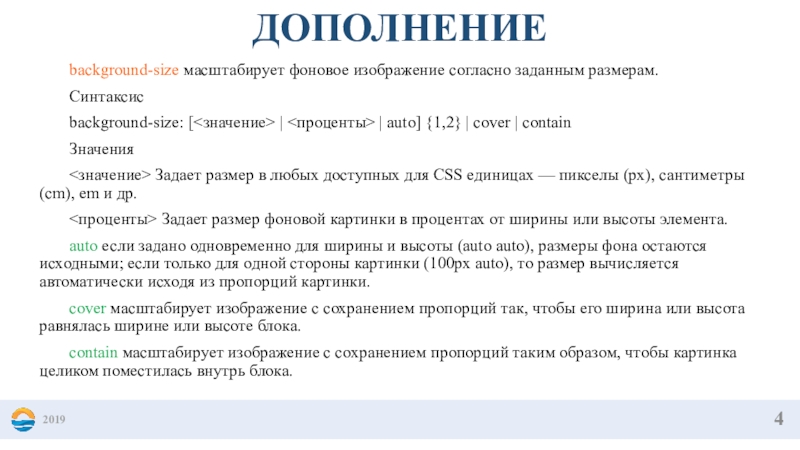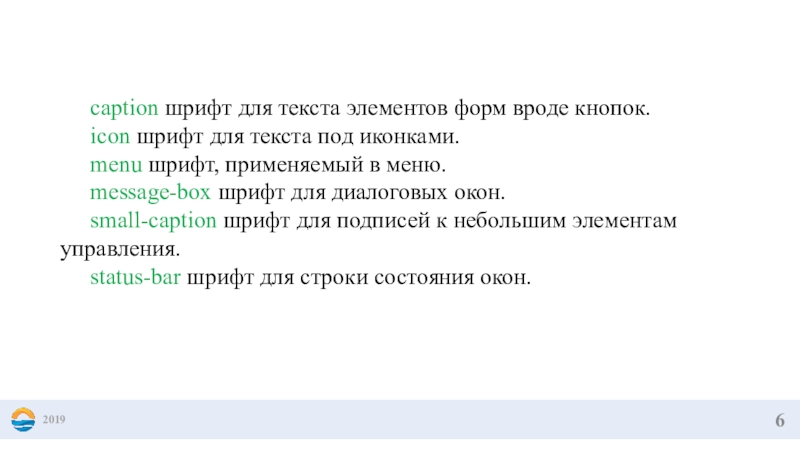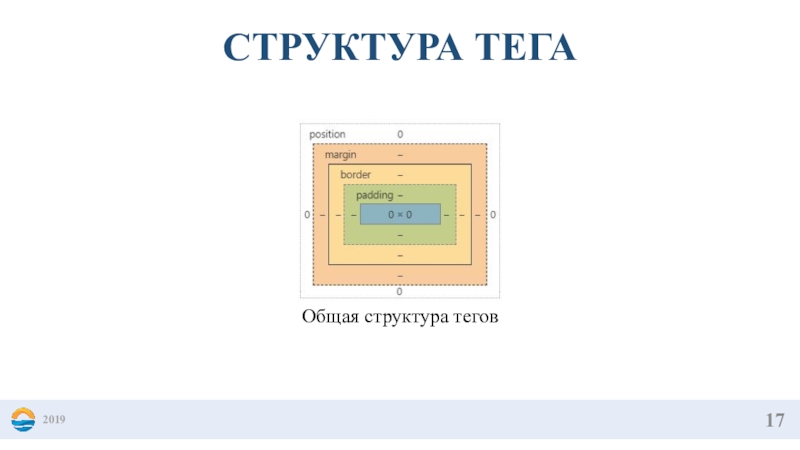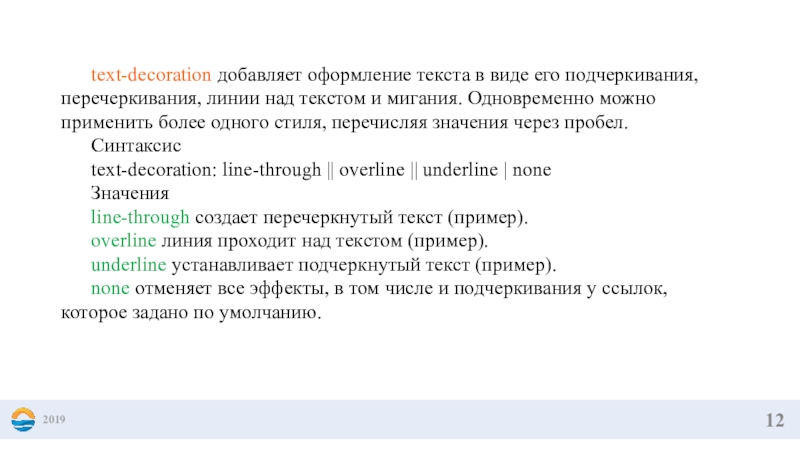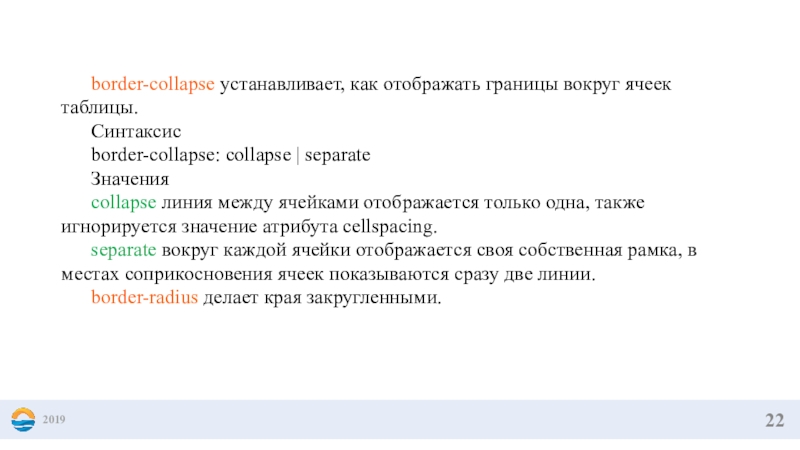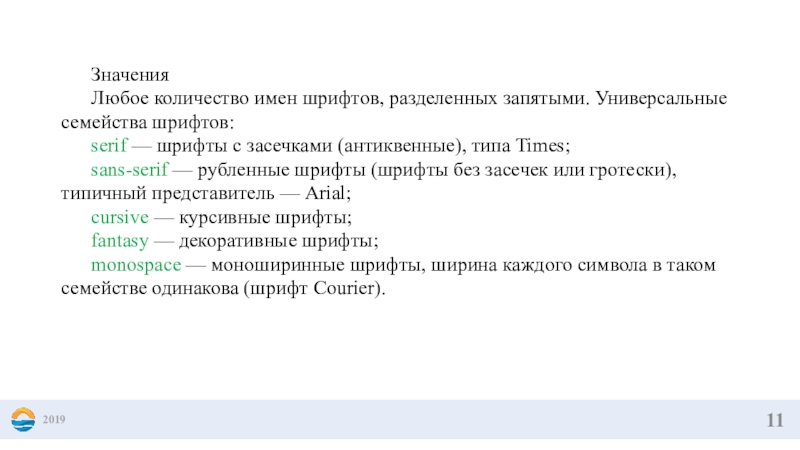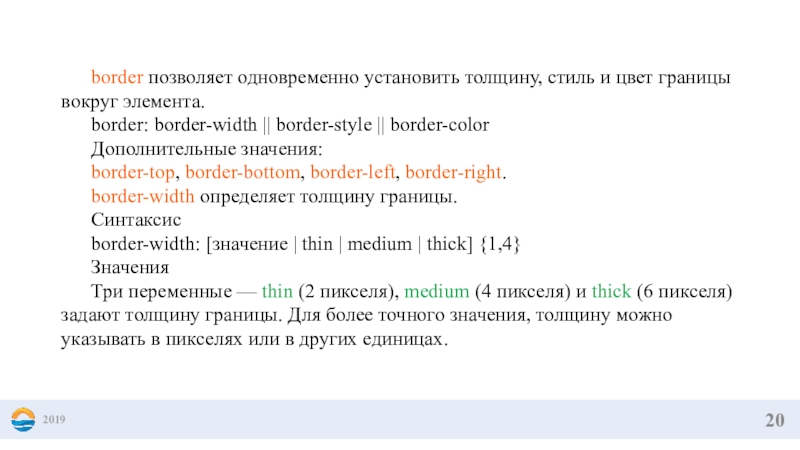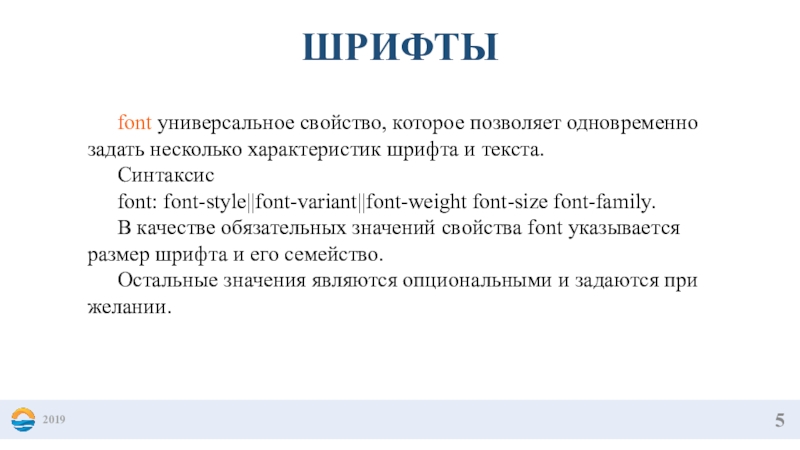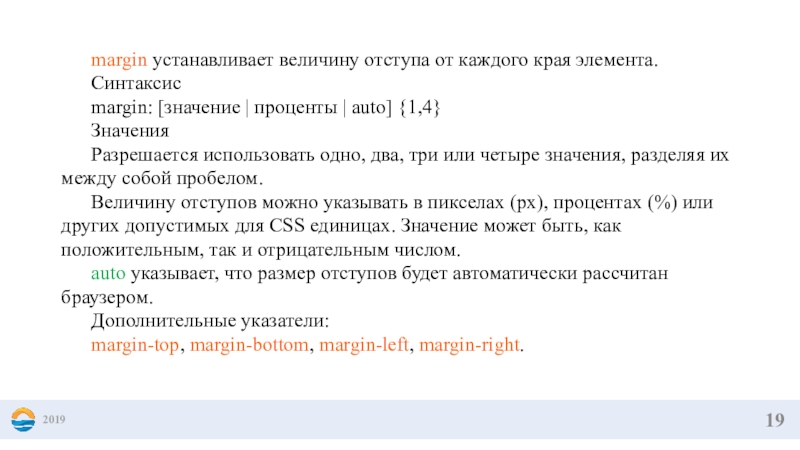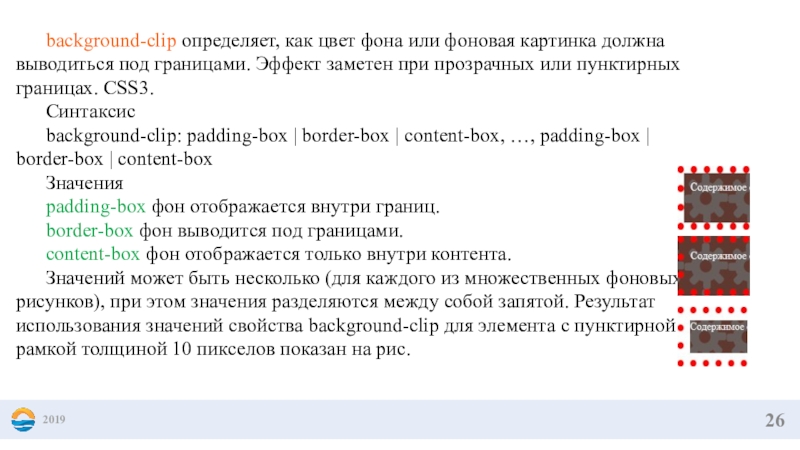
ШРИФТЫ. СТРУКТУРА ТЕГА
px – абсолютные пиксели, к которым привязаны и потому не
нужны mm, cm, pt и pc. Используется для максимально конкретного
и точного задания размеров.
em – задаёт размер относительно шрифта родителя, можно относительно конкретных символов: "x"(ex) и "0"(ch), используется там, где нужно упростить масштабирование компоненты.
pt – Точки традиционно используются в печатных изданиях (т.е. для всего, что печатается на бумаге). Одна точка равняется 1/72 дюйма. Точки очень похожи на пиксели тем, что они имеют фиксированный размер и их нельзя увеличить/уменьшить.
% – относительно такого же свойства родителя (как правило, но не всегда), используется для ширин, высот и так далее, без него никуда, но надо знать, относительно чего он считает проценты.
vw, vh, vmin, vmax – относительно размера экрана. Их основное преимущество – в том, что любые размеры, которые в них заданы, автоматически масштабируются при изменении размеров окна.
2019px – абсолютные пиксели, к которым привязаны и потому не нужны mm, cm, pt и pc. Используется
Слайд 4 background-size масштабирует фоновое изображение согласно заданным размерам.
Синтаксис
background-size: [ |
| auto] {1,2} | cover | contain
Значения
Задает размер в
любых доступных для CSS единицах — пикселы (px), сантиметры (cm), em и др.
<проценты> Задает размер фоновой картинки в процентах от ширины или высоты элемента.
auto если задано одновременно для ширины и высоты (auto auto), размеры фона остаются исходными; если только для одной стороны картинки (100px auto), то размер вычисляется автоматически исходя из пропорций картинки.
cover масштабирует изображение с сохранением пропорций так, чтобы его ширина или высота равнялась ширине или высоте блока.
contain масштабирует изображение с сохранением пропорций таким образом, чтобы картинка целиком поместилась внутрь блока.
ДОПОЛНЕНИЕ
background-size масштабирует фоновое изображение согласно заданным размерам.	Синтаксис	background-size: [ | | auto] {1,2} | cover | contain	Значения	 Задает
ШРИФТЫ
font универсальное свойство, которое позволяет одновременно задать несколько характеристик шрифта
и текста.
Синтаксис
font: font-style||font-variant||font-weight font-size font-family.
В качестве обязательных значений свойства
font указывается размер шрифта и его семейство.
Остальные значения являются опциональными и задаются при желании.
2019ШРИФТЫ	font универсальное свойство, которое позволяет одновременно задать несколько характеристик шрифта и текста.	Синтаксис	font: font-style||font-variant||font-weight font-size font-family. 	В качестве
caption шрифт для текста элементов форм вроде кнопок.
icon шрифт для
текста под иконками.
menu шрифт, применяемый в меню.
message-box шрифт для диалоговых
окон.
small-caption шрифт для подписей к небольшим элементам управления.
status-bar шрифт для строки состояния окон.
2019	caption шрифт для текста элементов форм вроде кнопок.	icon шрифт для текста под иконками.	menu шрифт, применяемый в меню.	message-box
font-style определяет начертание шрифта — обычное, курсивное или наклонное.
Синтаксис
font-style: normal
| italic | oblique
Значения
normal обычное начертание текста. (по умолчанию).
italic
курсивное начертание.
oblique наклонное начертание. Курсив и наклонный шрифт при всей их похожести не одно и то же. Курсив — это специальный шрифт имитирующий рукописный, наклонный же образуется путем наклона обычных знаков вправо.
font-variant определяет, как нужно представлять строчные буквы — оставить их без модификаций или делать их все прописными уменьшенного размера. Такой способ изменения символов называется капителью.
Синтаксис
font-variant: normal | small-caps
Значения
normal оставляет регистр символов исходным, заданным по умолчанию.
small-caps модифицирует все строчные символы как заглавные уменьшенного размера.
2019	font-style определяет начертание шрифта — обычное, курсивное или наклонное.	Синтаксис	font-style: normal | italic | oblique 	Значения	normal обычное начертание
Слайд 82019
font-weight устанавливает насыщенность шрифта. Значение устанавливается от 100 до 900
с шагом 100. Сверхсветлое начертание, которое может отобразить браузер, имеет
значение 100, а сверхжирное — 900. Нормальное начертание шрифта (которое установлено по умолчанию) эквивалентно 400, стандартный полужирный текст — значению 700.
Синтаксис
font-weight: bold|bolder|lighter|normal|100|200|300|400|500|600|700|800|900
Значения
Насыщенность шрифта задаётся с помощью ключевых слов:
bold — полужирное начертание.
normal — нормальное начертание. (по умолчанию).
Также допустимо использовать условные единицы от 100 до 900.
Значения bolder и lighter изменяют жирность относительно насыщенности родителя, соответственно, в большую и меньшую сторону.
2019	font-weight устанавливает насыщенность шрифта. Значение устанавливается от 100 до 900 с шагом 100. Сверхсветлое начертание, которое может
Слайд 92019
font-size определяет размер шрифта элемента.
Синтаксис
font-size: абсолютный размер | относительный размер
| значение | проценты
Значения
Для задания абсолютного размера используются следующие
значения: xx-small, small, medium (по умолчанию), large, x-large, xx-large.
Относительный размер шрифта задается значениями larger и smaller.
Также разрешается использовать любые допустимые единицы CSS: em (высота шрифта элемента), ex (высота символа х), пункты (pt), пикселы (px), проценты (%) и др. За 100% берется размер шрифта родительского элемента. Отрицательные значения не допускаются.
2019	font-size определяет размер шрифта элемента.	Синтаксис	font-size: абсолютный размер | относительный размер | значение | проценты 	Значения	Для задания абсолютного
Слайд 102019
font-family устанавливает семейство шрифта, которое будет использоваться для оформления текста
содержимого.
Список шрифтов может включать одно или несколько названий, разделенных
запятой. Если в имени шрифта содержатся пробелы, например, Trebuchet MS, оно должно заключаться в одинарные или двойные кавычки.
Когда браузер встречает первый шрифт в списке, он проверяет его наличие на компьютере пользователя.
Если такого шрифта нет, берется следующее имя из списка и также анализируется на присутствие.
Поэтому несколько шрифтов увеличивает вероятность, что хотя бы один из них будет обнаружен на клиентском компьютере.
Заканчивают список обычно ключевым словом, которое описывает тип шрифта — serif, sans-serif, cursive, fantasy или monospace.
Таким образом, последовательность шрифтов лучше начинать с экзотических типов и заканчивать обобщенным именем, которое задает вид начертания.
Синтаксис
font-family: имя шрифта, …, имя шрифта
2019	font-family устанавливает семейство шрифта, которое будет использоваться для оформления текста содержимого. 	Список шрифтов может включать одно или
Слайд 112019
Значения
Любое количество имен шрифтов, разделенных запятыми. Универсальные семейства шрифтов:
serif —
шрифты с засечками (антиквенные), типа Times;
sans-serif — рубленные шрифты (шрифты
без засечек или гротески), типичный представитель — Arial;
cursive — курсивные шрифты;
fantasy — декоративные шрифты;
monospace — моноширинные шрифты, ширина каждого символа в таком семействе одинакова (шрифт Courier).
2019	Значения	Любое количество имен шрифтов, разделенных запятыми. Универсальные семейства шрифтов:	serif — шрифты с засечками (антиквенные), типа Times;	sans-serif —
Слайд 122019
text-decoration добавляет оформление текста в виде его подчеркивания, перечеркивания, линии
над текстом и мигания. Одновременно можно применить более одного стиля,
перечисляя значения через пробел.
Синтаксис
text-decoration: line-through || overline || underline | none
Значения
line-through создает перечеркнутый текст (пример).
overline линия проходит над текстом (пример).
underline устанавливает подчеркнутый текст (пример).
none отменяет все эффекты, в том числе и подчеркивания у ссылок, которое задано по умолчанию.
2019	text-decoration добавляет оформление текста в виде его подчеркивания, перечеркивания, линии над текстом и мигания. Одновременно можно применить
Слайд 132019
text-align определяет горизонтальное выравнивание текста в пределах элемента.
Синтаксис
text-align: center |
justify | left | right | start | end
Значения
center выравнивание
текста по центру.
justify выравнивание по ширине, что означает одновременное выравнивание по левому и правому краю.
left выравнивание текста по левому краю. (по умолчанию)
right выравнивание текста по правому краю.
start аналогично значению left, если текст идёт слева направо и right, когда текст идёт справа налево.
end аналогично значению right, если текст идёт слева направо и left, когда текст идёт справа налево.
2019text-align определяет горизонтальное выравнивание текста в пределах элемента.Синтаксисtext-align: center | justify | left | right | start
Слайд 142019
text-indent устанавливает величину отступа первой строки блока текста (например, для
абзаца ). Воздействия на все остальные строки не оказывается. Допускается
отрицательное значение для создания выступа первой строки, но следует проверить, чтобы текст не выходил за пределы окна браузера.
Синтаксис
text-indent: <значение> | <проценты>
Значения
В качестве значений принимаются любые единицы длины, принятые в CSS — например, пикселы (px), дюймы (in), пункты (pt) и др. При задании значения в процентах, отступ первой строки вычисляется в зависимости от ширины блока. Допустимо использовать отрицательные значения, но при этом в разных браузерах возможно появление ошибок.
2019text-indent устанавливает величину отступа первой строки блока текста (например, для абзаца ). Воздействия на все остальные строки
Слайд 152019
text-shadow добавляет тень к тексту, а также устанавливает её параметры:
цвет тени, смещение относительно надписи и радиус размытия.
Синтаксис
text-shadow: none
| тень, …, тень
где тень: <сдвиг по x> <сдвиг по y> <радиус размытия> <цвет>
Значения
none отменяет добавление тени. (по умолчанию).
цвет тени в любом доступном CSS формате. По умолчанию цвет тени совпадает с цветом текста. Необязательный параметр.
сдвиг по x смещение тени по горизонтали относительно текста. Положительное значение этого параметра задает сдвиг тени вправо, отрицательное — влево. Обязательный параметр.
сдвиг по y смещение тени по вертикали относительно текста. Также допустимо использовать отрицательное значение, которое поднимает тень выше текста. Обязательный параметр.
радиус задает радиус размытия тени. Чем больше это значение, тем сильнее тень сглаживается, становится шире и светлее. Если этот параметр не задан, по умолчанию устанавливается равным 0. Учтите, что алгоритм сглаживания в браузерах обычно разный, поэтому вид тени может несколько различаться в зависимости от заданных параметров сглаживания.
Первая тень перекрывает остальные тени.
2019text-shadow добавляет тень к тексту, а также устанавливает её параметры: цвет тени, смещение относительно надписи и радиус
Слайд 162019
text-transform управляет преобразованием текста элемента в заглавные или прописные символы.
Когда значение отлично от none, регистр исходного текста будет изменен.
Синтаксис
text-transform:
capitalize | lowercase | uppercase | none
Значения
capitalize первый символ каждого слова в предложении будет заглавным. Остальные символы свой вид не меняют.
lowercase все символы текста становятся строчными (нижний регистр).
uppercase все символы текста становятся прописными (верхний регистр).
none не меняет регистр символов. (по умолчанию).
2019text-transform управляет преобразованием текста элемента в заглавные или прописные символы. Когда значение отлично от none, регистр исходного
Слайд 172019
СТРУКТУРА ТЕГА
Общая структура тегов
2019СТРУКТУРА ТЕГАОбщая структура тегов
Слайд 192019
margin устанавливает величину отступа от каждого края элемента.
Синтаксис
margin: [значение |
проценты | auto] {1,4}
Значения
Разрешается использовать одно, два, три или
четыре значения, разделяя их между собой пробелом.
Величину отступов можно указывать в пикселах (px), процентах (%) или других допустимых для CSS единицах. Значение может быть, как положительным, так и отрицательным числом.
auto указывает, что размер отступов будет автоматически рассчитан браузером.
Дополнительные указатели:
margin-top, margin-bottom, margin-left, margin-right.
2019	margin устанавливает величину отступа от каждого края элемента.	Синтаксис	margin: [значение | проценты | auto] {1,4} 	Значения	Разрешается использовать одно,
Слайд 202019
border позволяет одновременно установить толщину, стиль и цвет границы вокруг
элемента.
border: border-width || border-style || border-color
Дополнительные значения:
border-top, border-bottom, border-left, border-right.
border-width
определяет толщину границы.
Синтаксис
border-width: [значение | thin | medium | thick] {1,4}
Значения
Три переменные — thin (2 пикселя), medium (4 пикселя) и thick (6 пикселя) задают толщину границы. Для более точного значения, толщину можно указывать в пикселях или в других единицах.
2019	border позволяет одновременно установить толщину, стиль и цвет границы вокруг элемента.	border: border-width || border-style || border-color	Дополнительные значения:	border-top,
Слайд 212019
border-style для управления ее видом предоставляется несколько значений.
Синтаксис
border-style: [none
| hidden | dotted | dashed | solid | double
| groove | ridge | inset | outset] {1,4}
Значения
Их названия и результат действия представлен
border-color устанавливает цвет границы, значение может быть в любом допустимом для CSS формате.
2019	border-style для управления ее видом предоставляется несколько значений. 	Синтаксис	border-style: [none | hidden | dotted | dashed |
Слайд 222019
border-collapse устанавливает, как отображать границы вокруг ячеек таблицы.
Синтаксис
border-collapse: collapse |
separate
Значения
collapse линия между ячейками отображается только одна, также игнорируется
значение атрибута cellspacing.
separate вокруг каждой ячейки отображается своя собственная рамка, в местах соприкосновения ячеек показываются сразу две линии.
border-radius делает края закругленными.
2019	border-collapse устанавливает, как отображать границы вокруг ячеек таблицы.	Синтаксис	border-collapse: collapse | separate 	Значения	collapse линия между ячейками отображается только
Слайд 232019
padding устанавливает значение полей вокруг содержимого элемента.
Синтаксис
padding: [значение | проценты]
{1, 4}
Дополнительные значения:
padding-top, padding-bottom, padding-left, padding-right.
width устанавливает ширину блочных
или заменяемых элементов.
height устанавливает высоту блочных или заменяемых элементов.
max-width устанавливает максимальную ширину элемента.
max-height устанавливает максимальную высоту элемента.
min-width устанавливает минимальную ширину элемента.
min-height задает минимальную высоту элемента.
2019	padding устанавливает значение полей вокруг содержимого элемента.	Синтаксис	padding: [значение | проценты] {1, 4} 	Дополнительные значения:	padding-top, padding-bottom, padding-left, padding-right.	width
Слайд 242019
box-shadow добавляет тень к элементу. Допускается использовать несколько теней, указывая
их параметры через запятую, при наложении теней первая тень в
списке будет выше, последняя ниже. Если для элемента задается радиус скругления через свойство border-radius, то тень также получится с закругленными уголками. CSS3.
Синтаксис
box-shadow: none | <тень>, …, <тень>
где <тень>: inset <сдвиг по x> <сдвиг по y> <радиус размытия> <растяжение> <цвет>
Значения
none отменяет добавление тени. (по умолчанию).
inset тень выводится внутри элемента. Необязательный параметр.
сдвиг по x смещение тени по горизонтали относительно элемента. Положительное значение этого параметра задает сдвиг тени вправо, отрицательное — влево. Обязательный параметр.
сдвиг по y смещение тени по вертикали относительно элемента. Положительное значение задает сдвиг тени вниз, отрицательное — вверх. Обязательный параметр.
размытие задает радиус размытия тени. Чем больше это значение, тем сильнее тень сглаживается, становится шире и светлее. Если этот параметр не задан, по умолчанию устанавливается равным 0, тень при этом будет четкой, а не размытой.
растяжение положительное значение растягивает тень, отрицательное, наоборот, ее сжимает. Если этот параметр не задан, по умолчанию устанавливается 0, при этом тень будет того же размера, что и элемент.
цвет тени в любом доступном CSS формате, по умолчанию тень черная. Необязательный параметр.
2019	box-shadow добавляет тень к элементу. Допускается использовать несколько теней, указывая их параметры через запятую, при наложении теней
Слайд 252019
box-sizing применяется для изменения алгоритма расчета ширины и высоты элемента.
CSS3.
Синтаксис
box-sizing: content-box | border-box | padding-box
Значения
content-box основывается на стандартах CSS,
при этом свойства width и height задают ширину и высоту контента и не включают в себя значения отступов, полей и границ.
border-box свойства width и height включают в себя значения полей и границ, но не отступов (margin). Эта модель используется браузером Internet Exporer в режиме несовместимости.
padding-box свойства width и height включают в себя значения полей, но не отступов (margin) и границ (border).
2019	box-sizing применяется для изменения алгоритма расчета ширины и высоты элемента. CSS3.	Синтаксис	box-sizing: content-box | border-box | padding-box	Значения	content-box основывается
Слайд 262019
background-clip определяет, как цвет фона или фоновая картинка должна выводиться
под границами. Эффект заметен при прозрачных или пунктирных границах. CSS3.
Синтаксис
background-clip:
padding-box | border-box | content-box, …, padding-box | border-box | content-box
Значения
padding-box фон отображается внутри границ.
border-box фон выводится под границами.
content-box фон отображается только внутри контента.
Значений может быть несколько (для каждого из множественных фоновых рисунков), при этом значения разделяются между собой запятой. Результат использования значений свойства background-clip для элемента с пунктирной рамкой толщиной 10 пикселов показан на рис.
2019	background-clip определяет, как цвет фона или фоновая картинка должна выводиться под границами. Эффект заметен при прозрачных или